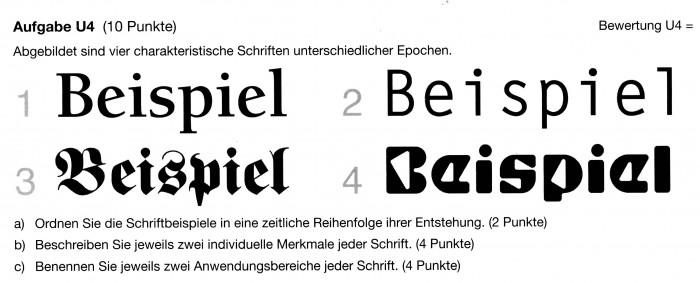
Fette Fraktur ist älter als die Venezianische Renaissance-Antiqua
Ich korrigiere gerade die Abschlussprüfung für den Beruf "Mediengestalter Digital und Print".
Und da wollte ich mal eine zweite Meinung einholen, weil die Musterlösung einer Aufgabe nach meiner Meinung falsch ist.
Es geht um die Teilaufgabe a)
Die Musterlösung ist: 3, 1, 2, 4
Findet das außer mir jemand merkwürdig?
Durchaus. Wenn bei der Fraktur der allgemeine Begriff »gebrochene Schrift« maßgeblich sein sollte, dann müßte bei der Renaissance-Antiqua auch der allgemeine Begriff »Antiqua« maßgeblich sein. Bei beiden Begriffspaaren (Antiqua vs. gebrochene Schrift oder Renaissance-Antiqua vs. Fraktur) würde man zu einer anderen  Sortierung kommen, auch wenn man sich beim zweiten Begriffspaar vielleicht um ein paar Jahre streiten könnte.
Aber das falsche Schluß-s in Beiſpiel ist für eine Mediengestalter-Prüfung schon ziemlich starker Tobak.
Nicht, wenn man von den DIN-Klassifikationsgruppen ausgeht, die die Azubis hier bestimmt lernen mussten.
Ist ja nicht »falsch«, nur nicht »traditionell«.
Gefragt ist, die Entstehungszeiten der abgebildeten konkreten Schriftbeispiele in die richtige Reihenfolge zu bringen.
Hier wird nicht nach Schriftklassifizierungen gefragt, was übrigens zu zeitlichen Einordnung von Antiquas vs gebrochener Schriften wenig taugt, da sich diese zum Teil zeitlich parallel entwickelt haben.
Jedenfalls ist doch die abgebildete "Fette Fraktur" aus der Mitte des 19. Jahrhunderts. Und da wäre es doch zumindest denkbar, dass die abgebildete venezianische Renaissance-Antiqua älter sein könnte, oder?
Ist das spitzfindig? Genauso wie das falsche s in Beispiel? Immerhin ist der Mediengestalter der Nachfolger des Schriftsetzers …
Wenn dem so wäre, dann wäre die Fette Fraktur (1850) älter als die Berkeley (1983).
(Die Aufgabenstellung spricht aber nicht von konkreten Schriftbeispielen, sondern von charakteristischen Schriften vierer Epochen.)
Dann sollte aber die Frage entsprechend gestellt sein. Es sollen eben nicht die »Schriftbeispiele« geordnet werden (wie es da steht), sondern die Schriftstile. (Ersteres ist sowieso praktisch unmöglich.)
Aber vor 1996 war es eben tatsächlich falsch und bis ca. 1950 gänzlich unüblich. Es gab zwar sehr vereinzelte Ausnahmen davor, aber wenn mich jemand bäte dieses Schriftbeispiel zeitlich einzuordnen, wäre meine Antwort, dass es zu 99,9 % nach 1950 entstanden sei.
Ich versuche ja auch nur zu deuten, wie es gemeint sein könnte. Letztlich prüft die Frage ja etwas ab, was vorher gelehrt wurde. Ohne diese Inhalte zu kennen, kann man sicherlich sagen, dass die Frage zu unklar ist und und verschiedene Antwortkombinationen möglich sind.
Wenn Beispiel 1 die Berkley ist, dann stimmt ja die Reihenfolge der Musterlösung.
Nein, dies geht davon aus, dass die Entstehungszeit der individuellen Schriften gefragt ist. Dann wäre aber die korrekte Reihenfolge (vorausgesetzt ich habe alle korrekt identifiziert):
• Fette Fraktur (1850, 3)
• Letter Gothic (1962, 2)
• Berkeley (1983, 1) – andererseits ist die wiederum aus der University of California Old Style (1938) entstanden
• Shuriken Boy (1996, 4)
So oder so kann niemand ernsthaft von den Prüflingen erwarten, alle Schriften zu identifizieren und auch noch das Entstehungsjahr zu kennen.
Ich könnte mich auch noch auf den Standpunkt stellen, dass die Entstehungszeit der tatsächlichen Beispiele gefragt ist. Dann wäre die korrekte Antwort die Reihenfolge, in der der Mensch, der die Aufgabe erstellt hat, die Beispiele gebastelt hat (und also unbekannt).
Zumindest wäre es aber zutiefst ungerecht, die Antwort dann als falsch zu werten, wenn der Prüfling jetzt es tatsächlich hin bekommt, die abgebildeten konkreten Schriften genau zu bestimmen, und davon zufällig auch das zumindest ungefähre Erstellungsjahr weiß.
Gute Lehrer würde Extrapunkte geben für eine schlüssige Alternativlösung. Diese bedürfte allerdings der Erläuterung – ist die Frage, ob dafür in Multiple-Choice-Prüfungen Platz ist.
Es sollte eigentlich nicht zum Schaden der Prüflinge sein, deren richtige Antwort an von der Musterlösung abweicht.
Ich habe aber leise Zweifel, dass das alle Prüfer bei dieser bundesweit einheitlichen Prüfung berücksichtigen werden …
Dieser Prüfungsteil ist übrigens nicht Multiple Choice.